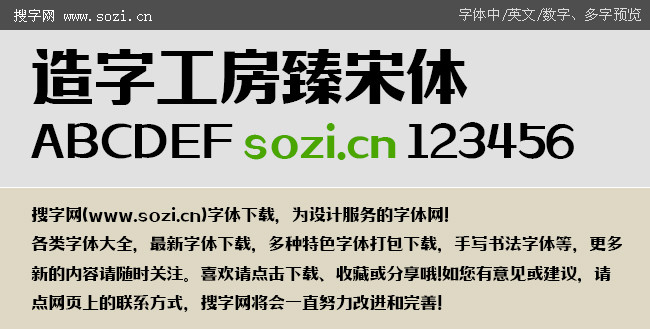
造字工房臻宋體
搜字網(wǎng)給大家提供一款造字工房臻宋體中文字體下載,造字工房臻宋體字體形體方正,筆畫簡(jiǎn)爽,豐腴跌宕,結(jié)體剛勁峻拔,方潤(rùn)整齊,整體風(fēng)格寬綽開張、婉雅秀逸。適合應(yīng)用于書籍裝幀設(shè)計(jì)、包裝設(shè)計(jì)、海報(bào)設(shè)計(jì)、網(wǎng)頁(yè)設(shè)計(jì)等應(yīng)用。(本字體為個(gè)人非商用版,如需要商用請(qǐng)聯(lián)系官方購(gòu)買版權(quán))